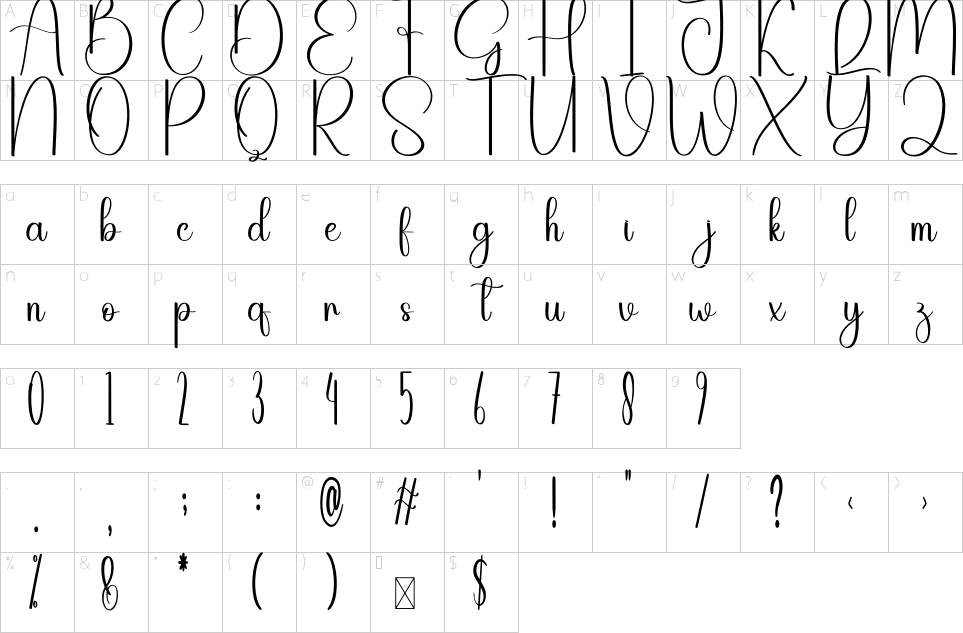
Descubra a sua nova favorita entre as fontes gratuitas para Windows e Mac com nossa Greeting Font. Esta elegante escolha foi projetada pelo talentoso scratchones, disponível para quem busca uma fonte personalizada e de fácil uso no dia a dia. Com 448 downloads desde que lançamos esta hermosa fonte, é óbvio que muitos usuários estão encantados com sua facilidade de aplicação e beleza. Experimente Greeting Font na sua próxima criação visual e veja por si mesmo o impacto da elegância desta fonte no seu design.